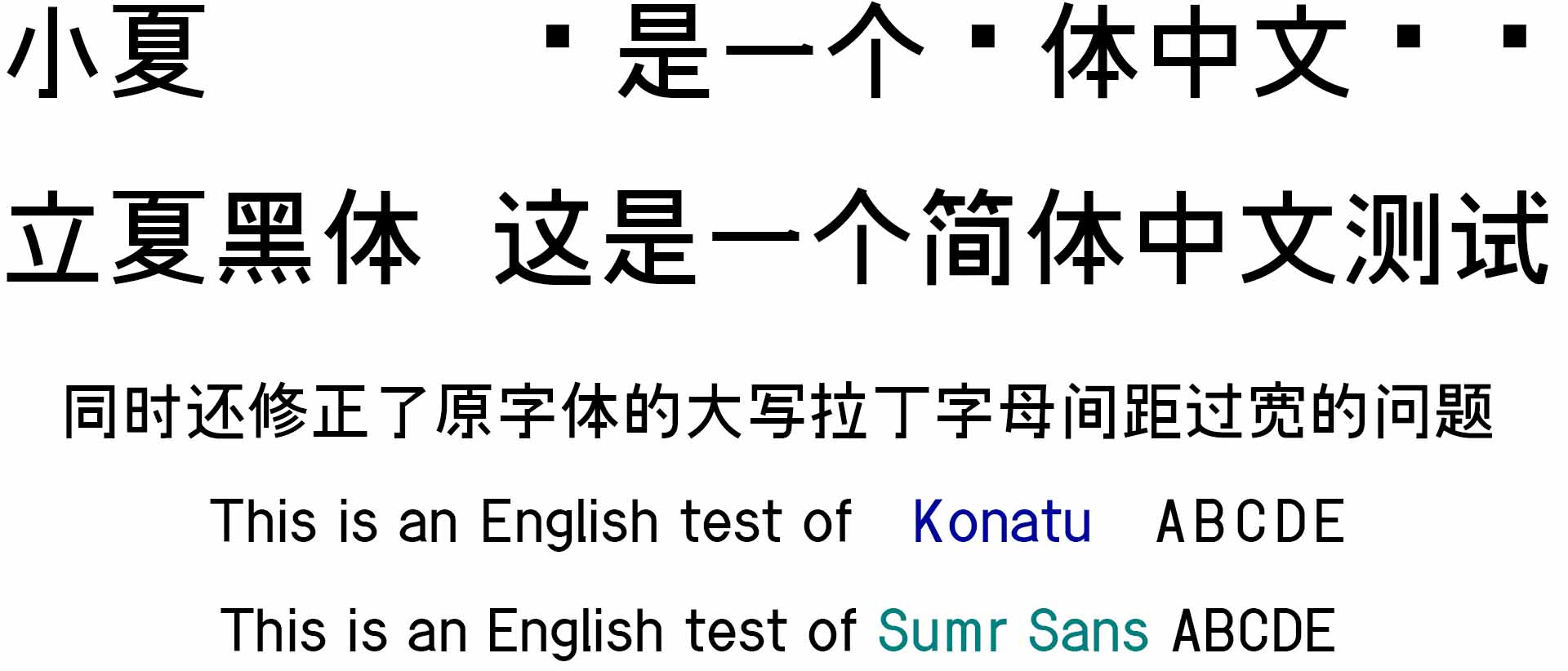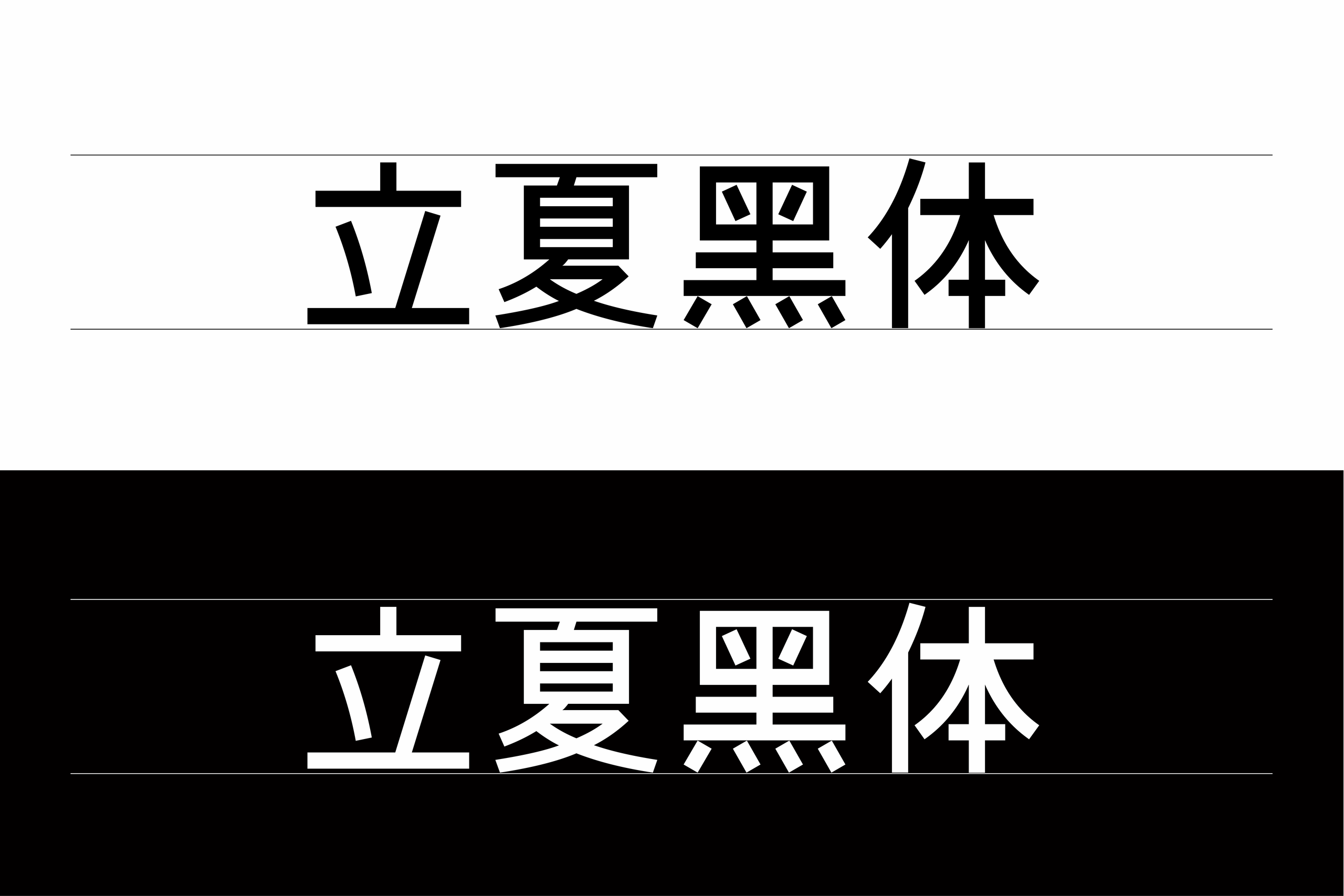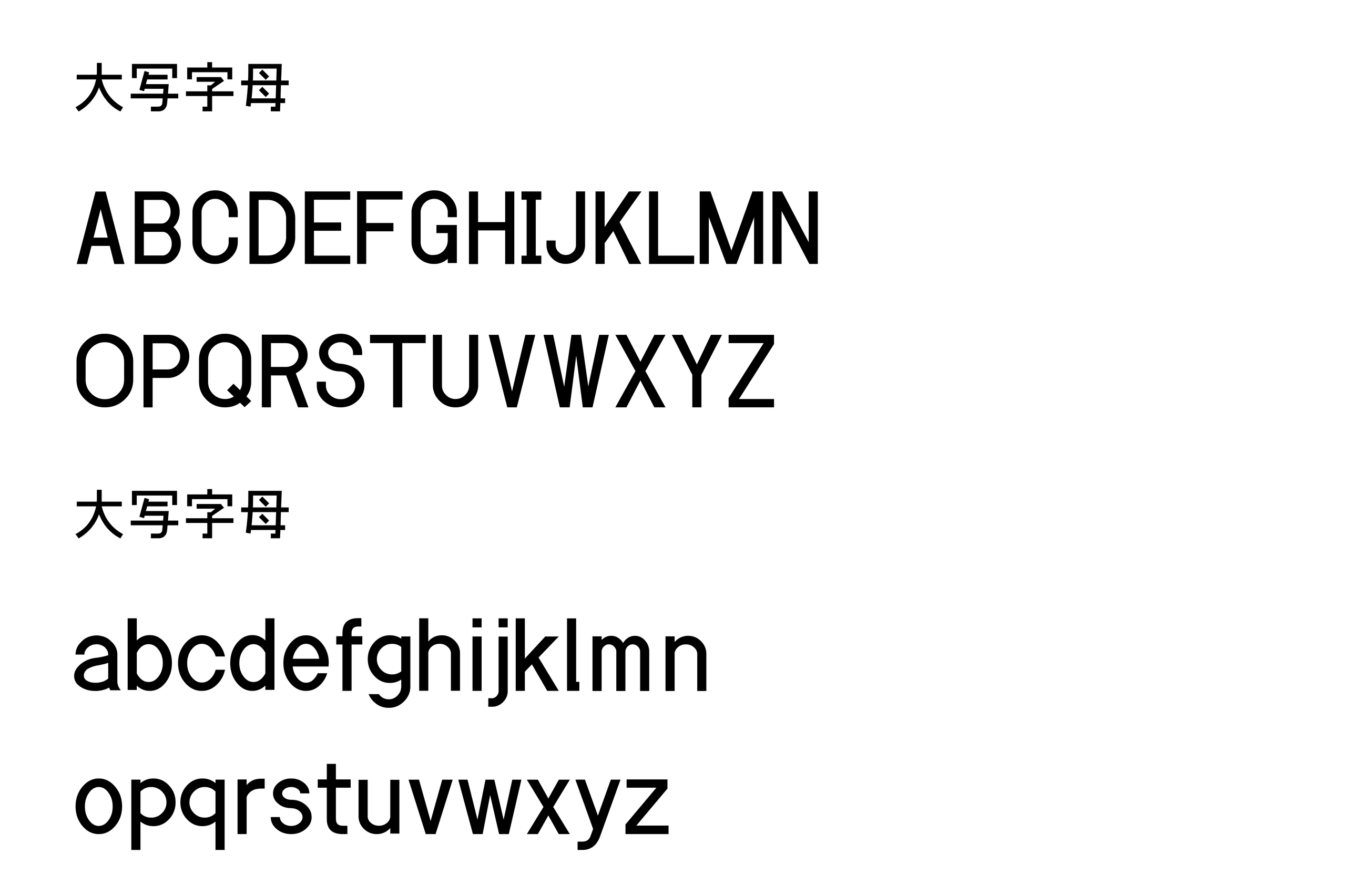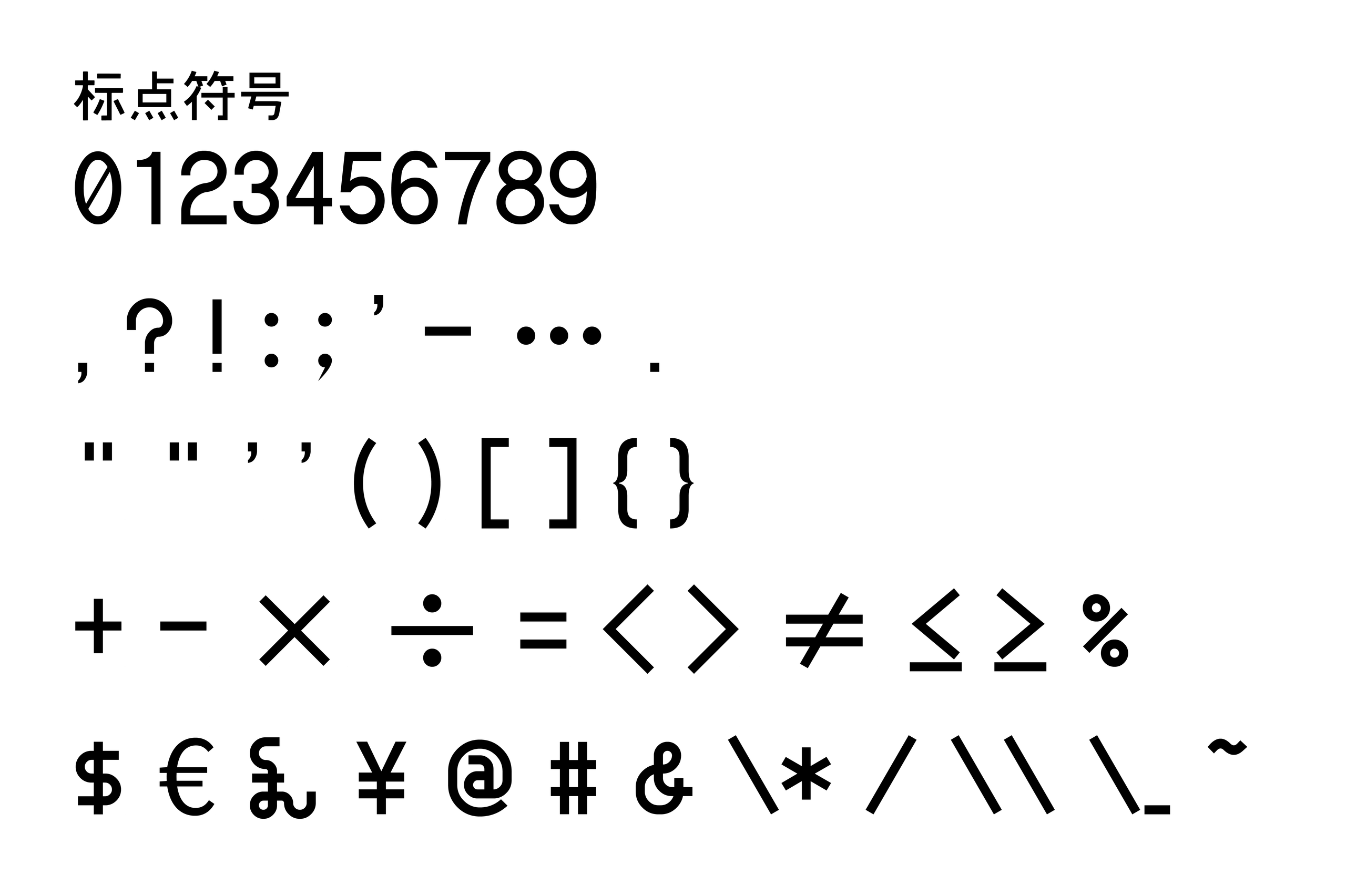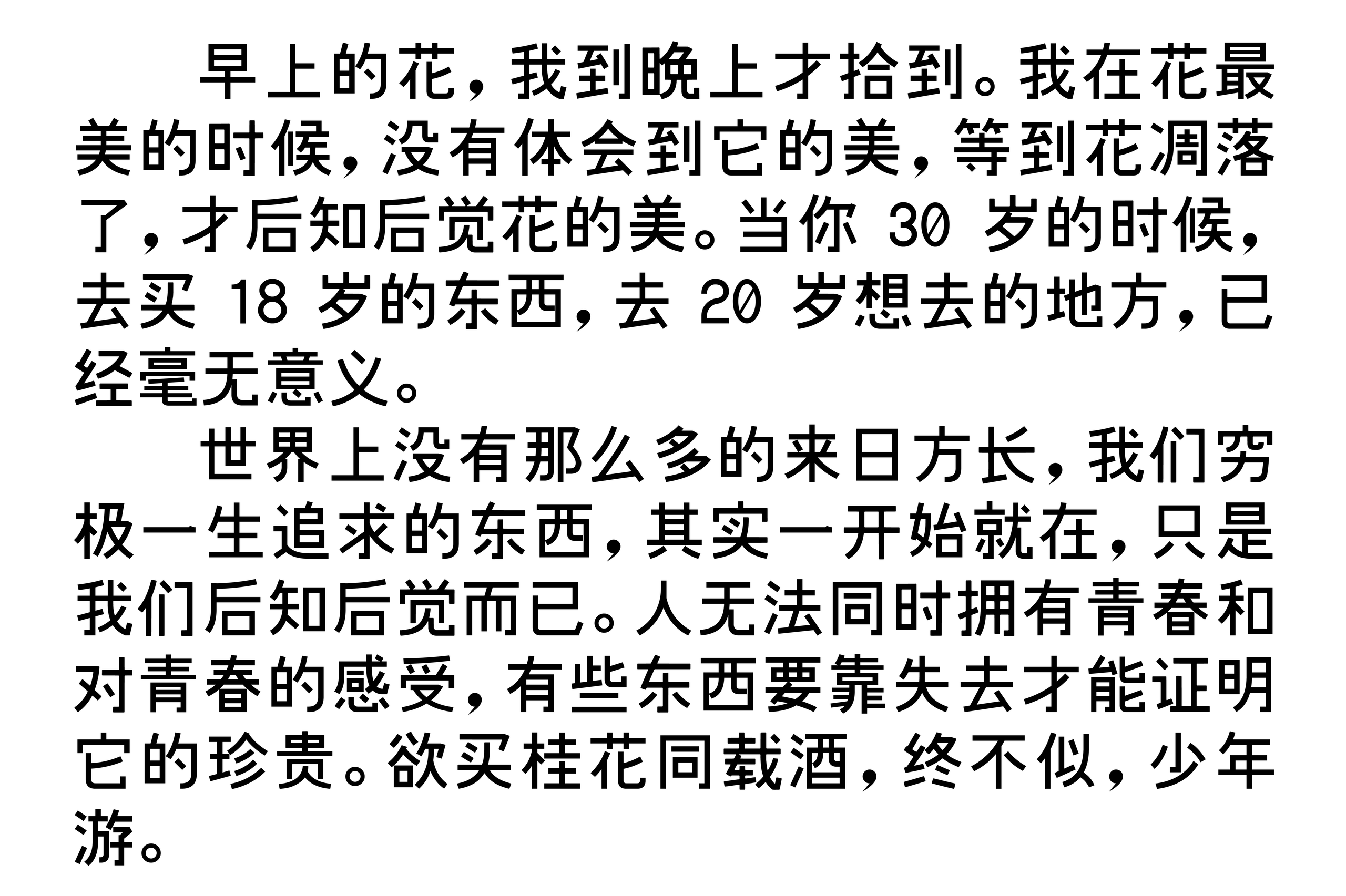
立夏黑体
立夏黑体(Sumr Sans)是一款基于小夏字体进行汉字增补的开源中文黑体。字体整体采用简洁利落的无衬线结构,字形规整,笔画清晰,在保持黑体易读性的同时融入了一定的几何感,整体视觉简洁而现代,适合用于标题、海报、网页以及各类视觉设计。
从字形表现来看,立夏黑体延续了小夏字体简洁的设计基础,并针对中文字符进行了大规模补充。字体使用 zi2zi-JiT 训练原字体的风格,同时参考文渊黑体、文渊宋体的字形结构进行补字,使扩展后的汉字在结构和视觉风格上尽量保持统一。
立夏黑体的中文笔画较为简洁,横竖结构明确,整体字面保持舒展的比例。部分字形具有明显的几何化处理,在大字号下能够呈现出较为清晰的轮廓和利落的视觉效果。字体并没有加入复杂的装饰元素,因此整体风格比较克制,更适合现代平面设计与数字场景。
在拉丁字符方面,立夏黑体同时包含大写和小写英文字母。大写字母采用简洁的无衬线结构,部分字形带有较明显的几何特征;小写字母则保持自然、简洁的字面关系,与中文字符搭配时能够形成统一的视觉节奏。英文字母、数字及常用符号适合用于标题中的中英文混排,也可以用于海报中的辅助文字设计。
字符覆盖方面,立夏黑体目前已经覆盖绝大部分 GB2312 字符,并继续扩充现代汉语常用字表、现代汉语通用字表、义务教育语文课程常用字表以及通用规范汉字表。同时还加入了落霞孤鹜外字初步整理表(第一部分)、绵饴字集以及 NAF194中的部分字符,因此除了常用汉字之外,也具备一定的扩展字符覆盖能力。
需要注意的是,由于部分汉字通过程序辅助生成,目前仍有少量复杂、生僻字符没有收录,部分生成字形也可能存在结构不协调、轮廓点较多或个别笔画错误等情况。作者目前仍在持续对字体进行人工检查和字形调整,后续将进一步修改字形,使其逐步符合国标规范。因此在正式设计使用时,建议针对实际文字内容进行字符检查。
在实际应用中,立夏黑体简洁规整的字形比较适合海报标题、品牌视觉、网页设计、UI 界面、社交媒体配图、电商设计、宣传物料以及日常排版等场景。较为鲜明的黑体结构在大字号标题中具有不错的视觉表现,而简洁的英文字符也能够满足中英文混排需求。
总体来看,立夏黑体是一款以中文字符扩展和开源使用为主要特点的现代黑体字体。它在小夏字体的基础上进一步完善中文字符覆盖,同时提供较为简洁的中英文视觉表现,对于需要免费商用中文黑体的设计项目具有一定的实用价值。